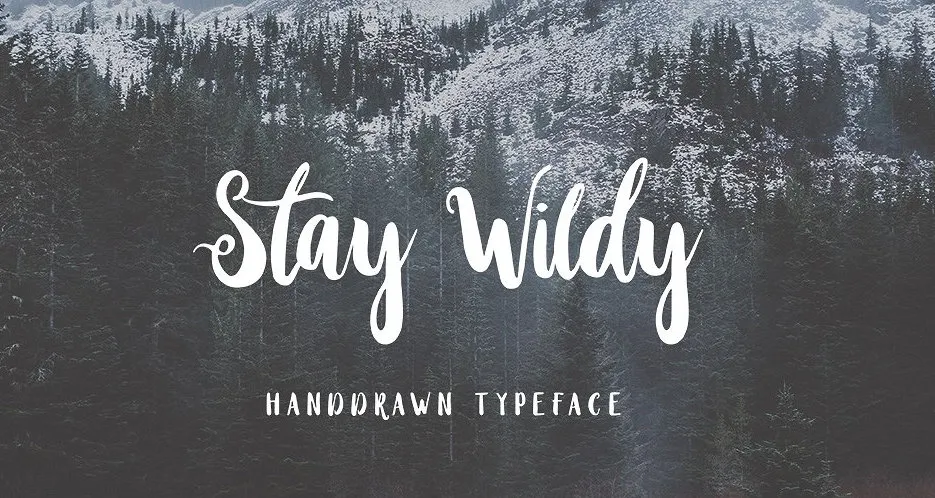
Stay Wildy Script Font – Download Grátis
Descubra a arte viva do “Stay Wildy Script Font” com Hamilton, designer responsável por esta incrível fonte script. Inspirada em uma escrita manual contemporânea e moderna, ela é uma perfeita escolha para quem quer dar um toque autêntico aos seus projetos de design tipográfico. Esta fonte vem com apenas um estilo básico, mas a surpresa vem quando você usa letras maiúsculas – o texto ganha um aspecto do tipo sans-serif e transmite a sensação de duas diferentes fontes. Perfecta para crear diseños de tipografía, cartas de Navidad, branding y logos, paquetes de productos, invitaciones, citas, camisetas, paneles de etiquetado e carteirinhas. Este diseño original del estilo “Stay Wildy Script Font” diseñado por DikasStudio captura la esencia de la creatividad moderna sin perder su personalidad auténtica y versátil. ¿Estás listo para explorar las posibilidades de esta font que se adapta perfectamente a tus proyectos? Descarga “Stay Wildy Script Font” hoy mismo y empieza a hacer tu trabajo brillar con una nueva perspectiva única.